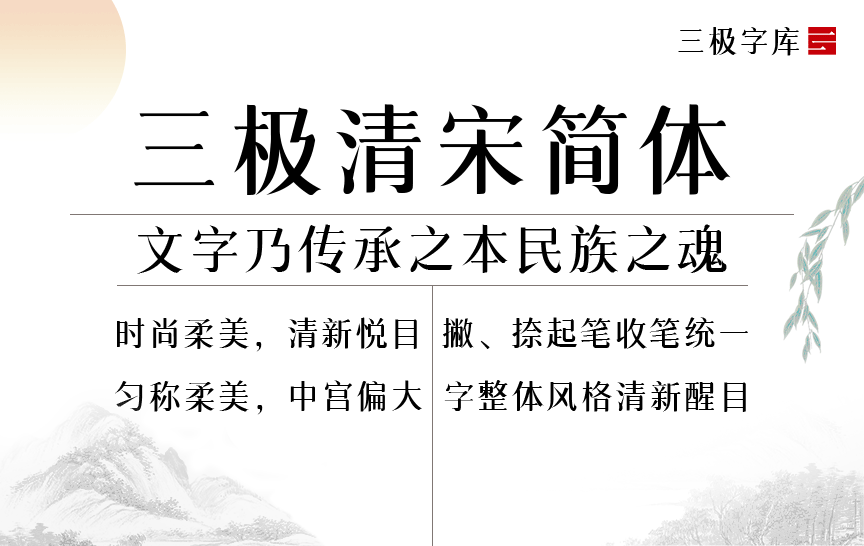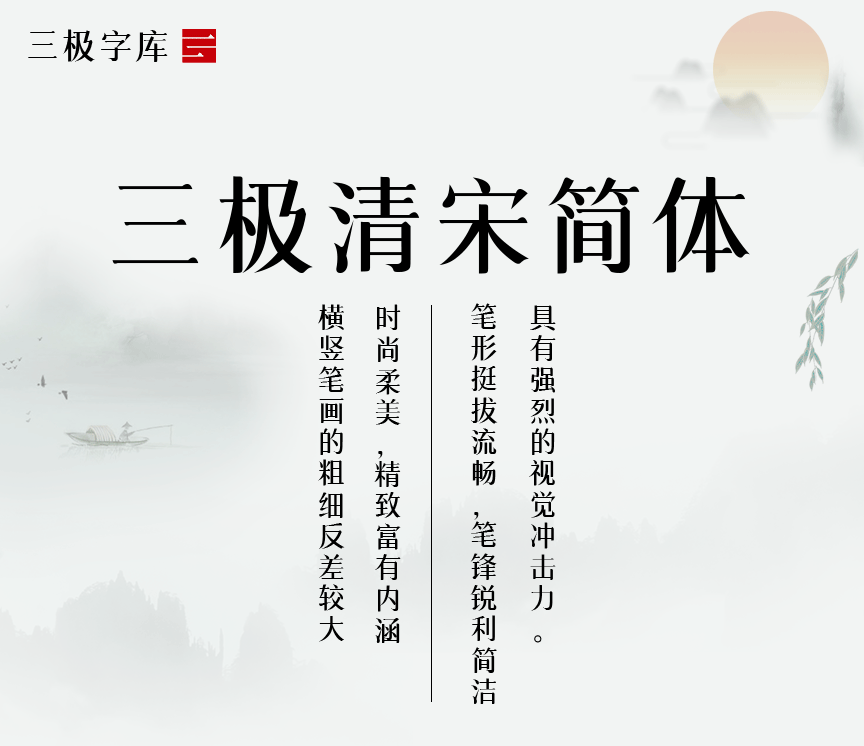
三极清宋简体是一款家族字体,其字形清新,布白均匀,字形结构饱满匀称、柔美,中宫偏大,笔形挺拔流畅,笔锋锐利简洁。撇、捺起笔收笔统一,个性鲜明,富有朝气。这款字的整体风格清新醒目、时尚柔美,精致富有内涵。横竖笔画的粗细反差较大,具有强烈的视觉冲击力。不但适用于各类传统纸媒,还可直接用于屏幕阅读。适用于传统印刷媒介的标题与正文排版。以及广告、标志和产品包装设计。
适用媒介:报纸、杂志、书籍、广告、标志、宣传册、空间导视、包装、屏幕显示。